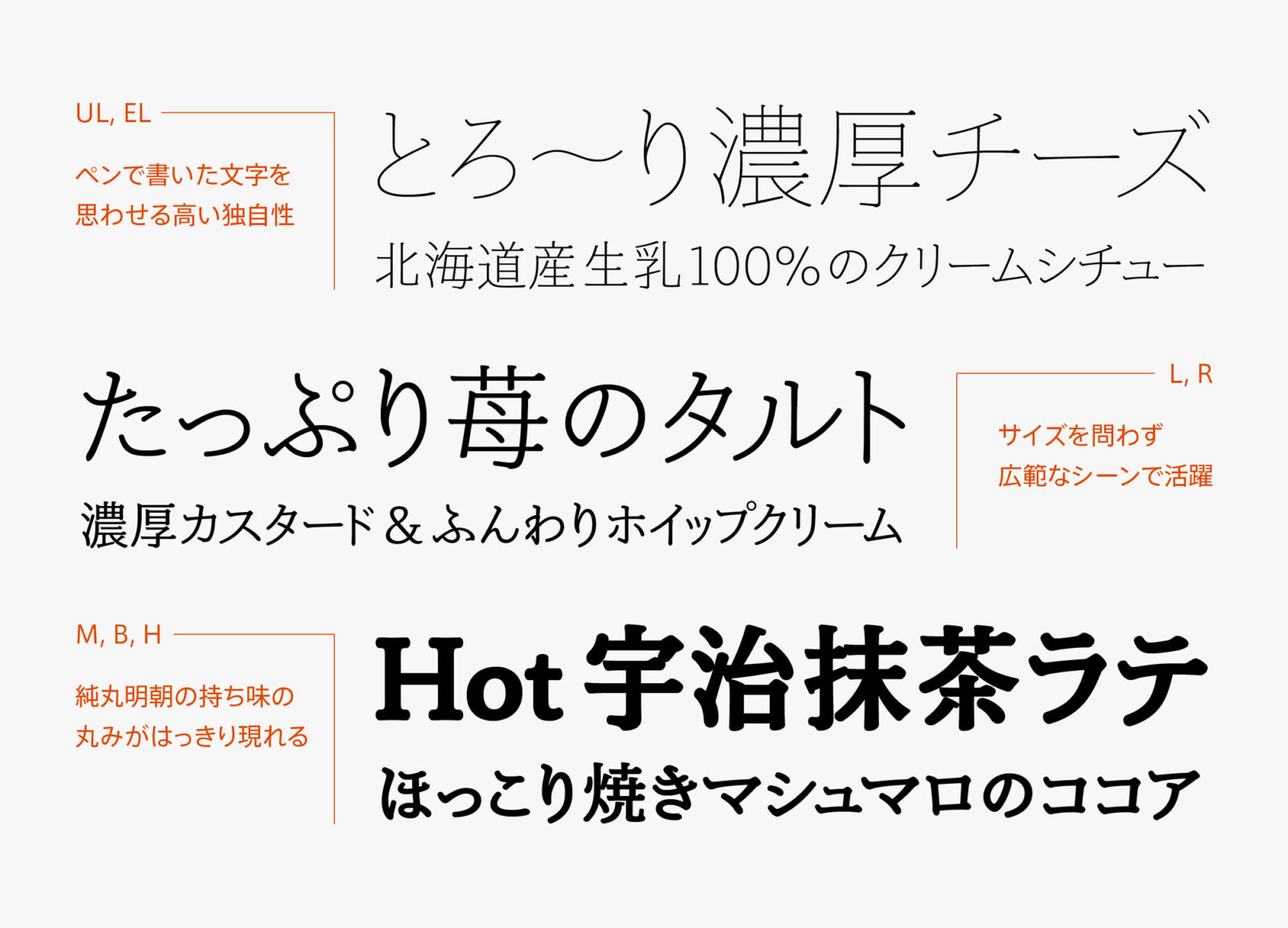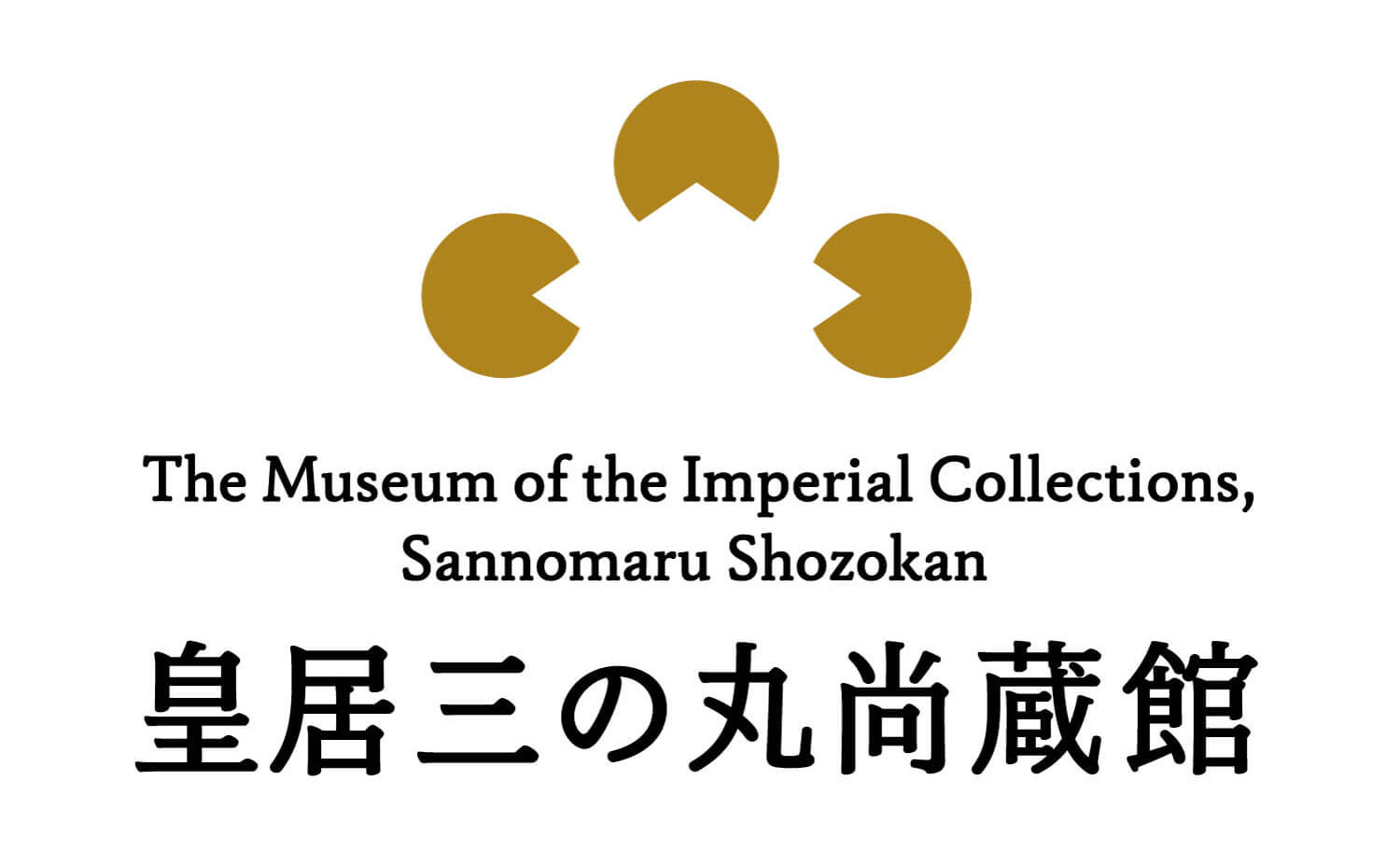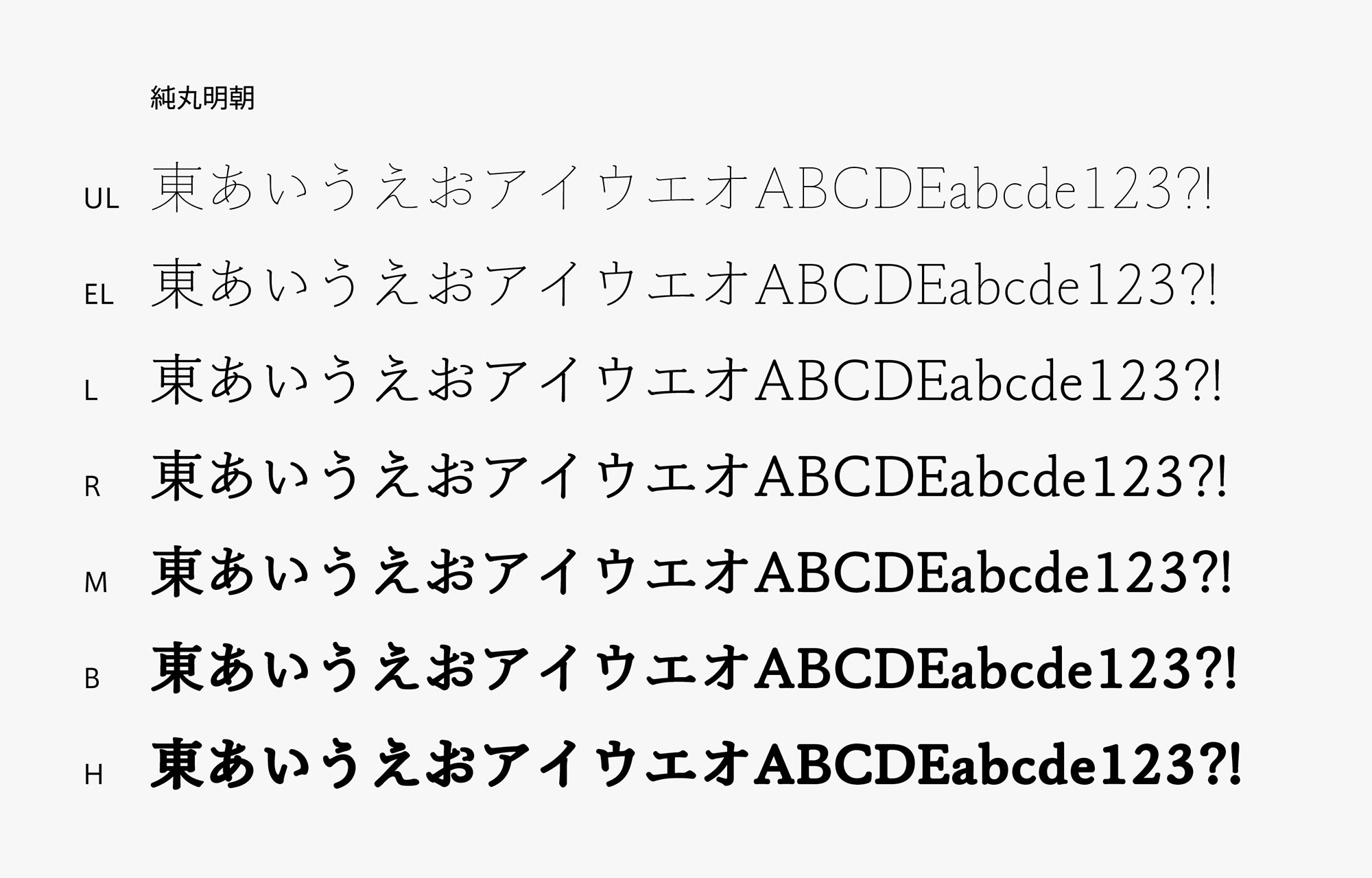
タイププロジェクト、オーソドックスで汎用性の高い純明朝をベースにした「純丸明朝」の提供を開始
皇居三の丸尚蔵館のロゴタイプに採用
タイププロジェクト株式会社(東京都練馬区 代表取締役社長 鈴木 功)は、端正な骨格を持ちながらも穏和で落ち着いた雰囲気を醸し出す明朝体「純丸明朝」を発表しました。本日よりタイププロジェクトのサブスクリプションサービス「TPコネクト」にて提供を開始いたします。
純丸明朝は、親しみやすいデザインでありながらも文字の骨格は端正で引き締まっており、魅力と信頼感を兼ね備えた書体です。明朝体の優美なシルエットを残し、読みやすく優しく、全体を通してマイルドで穏やかな表情で、書籍のタイトルから食品飲料のパッケージ、パンフレットからポスターに至るまで、さまざまなアイテムに安心して使用いただけます。
純丸明朝は、端正な骨格を持ちながらも穏和で落ち着いた雰囲気を醸し出す明朝体です。明朝特有の縦画と横画のコントラストを極限まで低減することでチラつきを抑え、小さいサイズでもしっかり文字を認識でき、画面上での高い表示適性を実現しています。
純丸明朝の和文書体および欧文書体は、株式会社日本デザインセンター 色部デザイン研究所がデザインした「皇居三の丸尚蔵館ロゴマーク」の書体として採用されています。
タイププロジェクトの代表取締役 鈴木 功は、「テンやハライの先端が太くて丸いのが純丸明朝の持ち味です。横画終端のおむすびのような丸いウロコは、あたたかみのある純丸明朝のキャラクターをよくあらわしてます。縦画と横画のコントラストはかなり低めに設定しましたが、ストロークの動きに伴う自然な抑揚はしっかり残しました。縦画と横画のコントラストを極力減らし、明朝体特有のチラつきを抑えた純丸明朝は、小さいサイズでもしっかり文字を認識できる表示適正の高い書体だと自負しています。サブスクリプションでの提供開始に先んじて、皇居三の丸尚蔵館のロゴタイプに採用されたことをとても嬉しく思います」と述べています。
純丸明朝ファミリーは、UL(ウルトラライト)、EL(エクストラライト)、L(ライト)、R(レギュラー)、M(ミディアム)、B(ボールド)、H(ヘヴィ)の7ウエイトで構成されています。読みやすくて優しい表情を見せる純丸明朝は、書籍のタイトルから食品飲料のパッケージ、パンフレットからポスターに至るまで、さまざまなアイテムに安心してご使用いただけるフォントです。